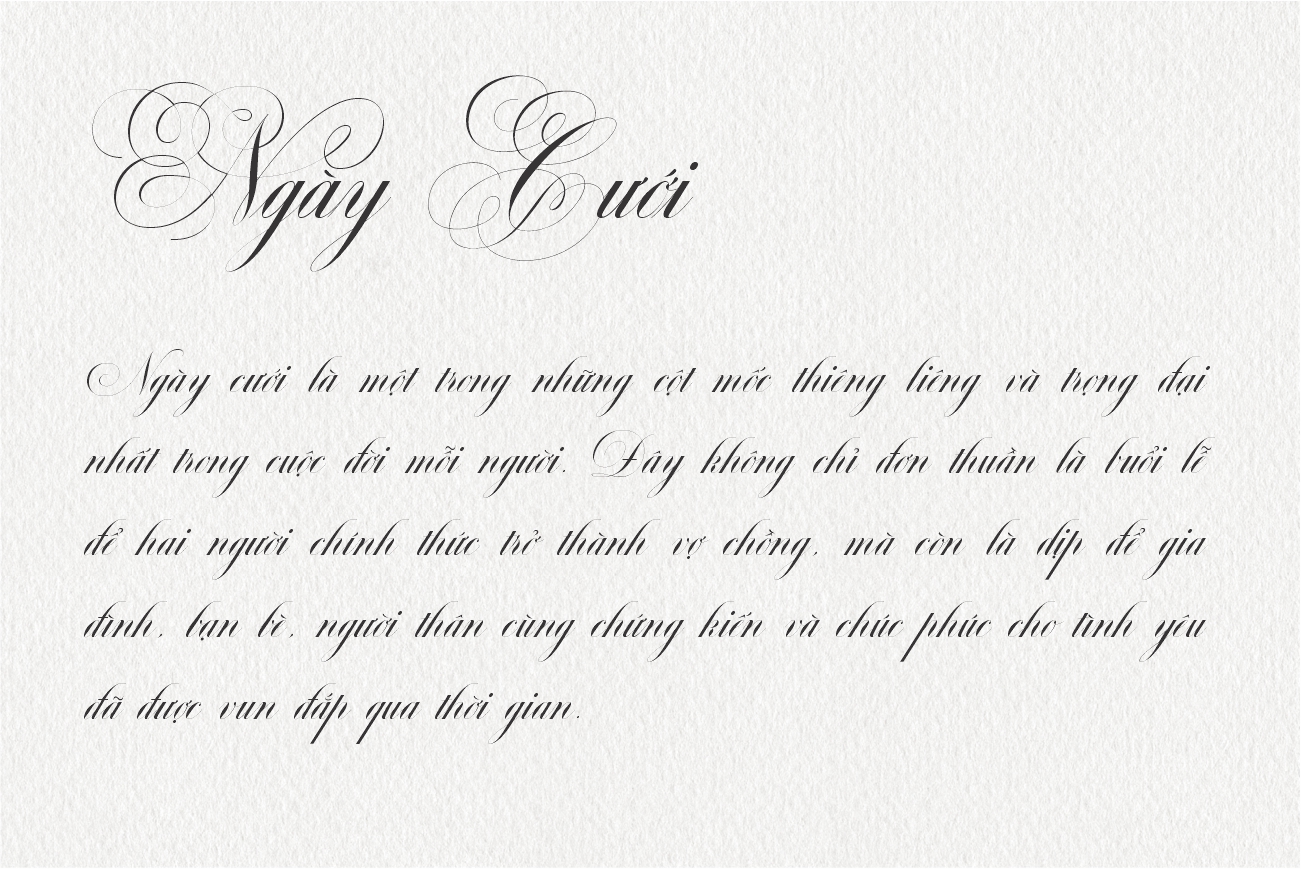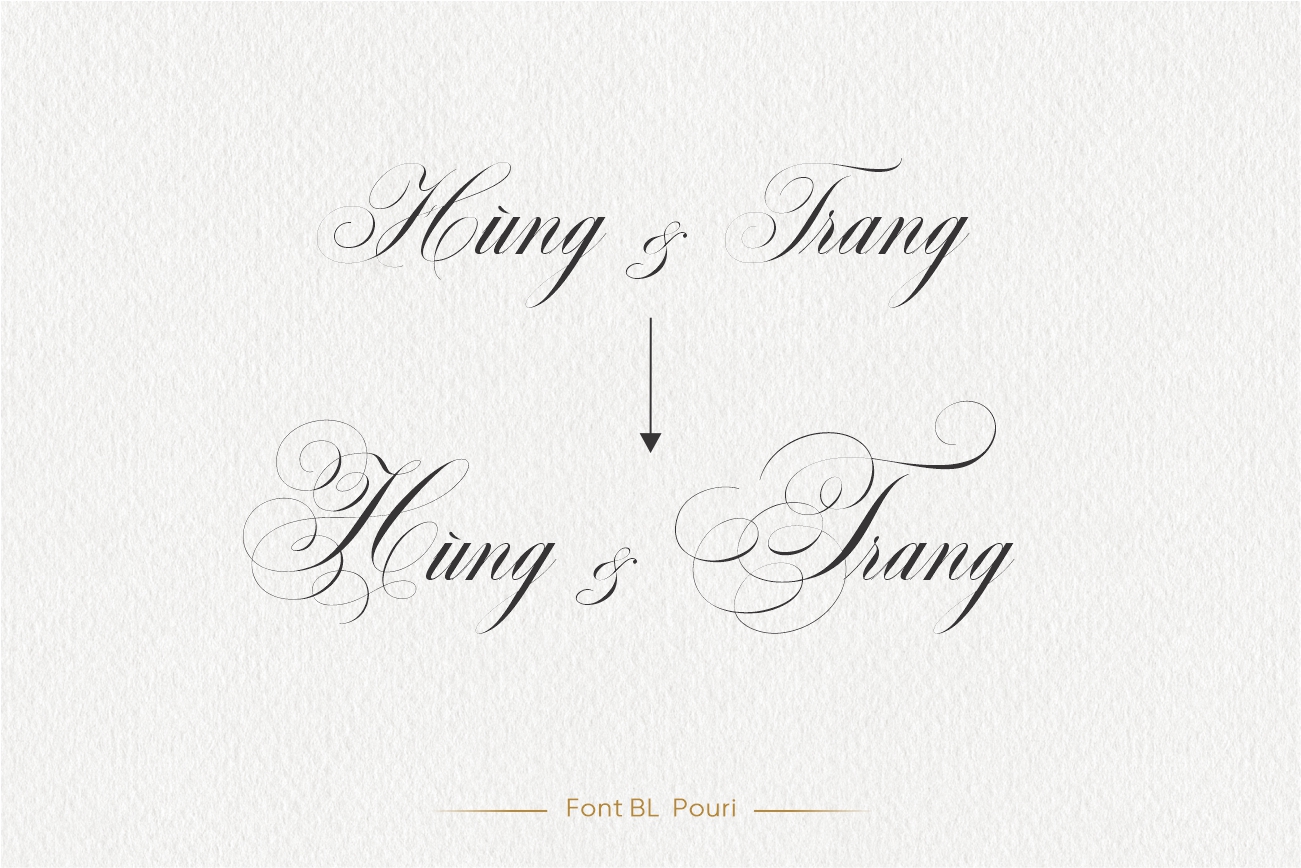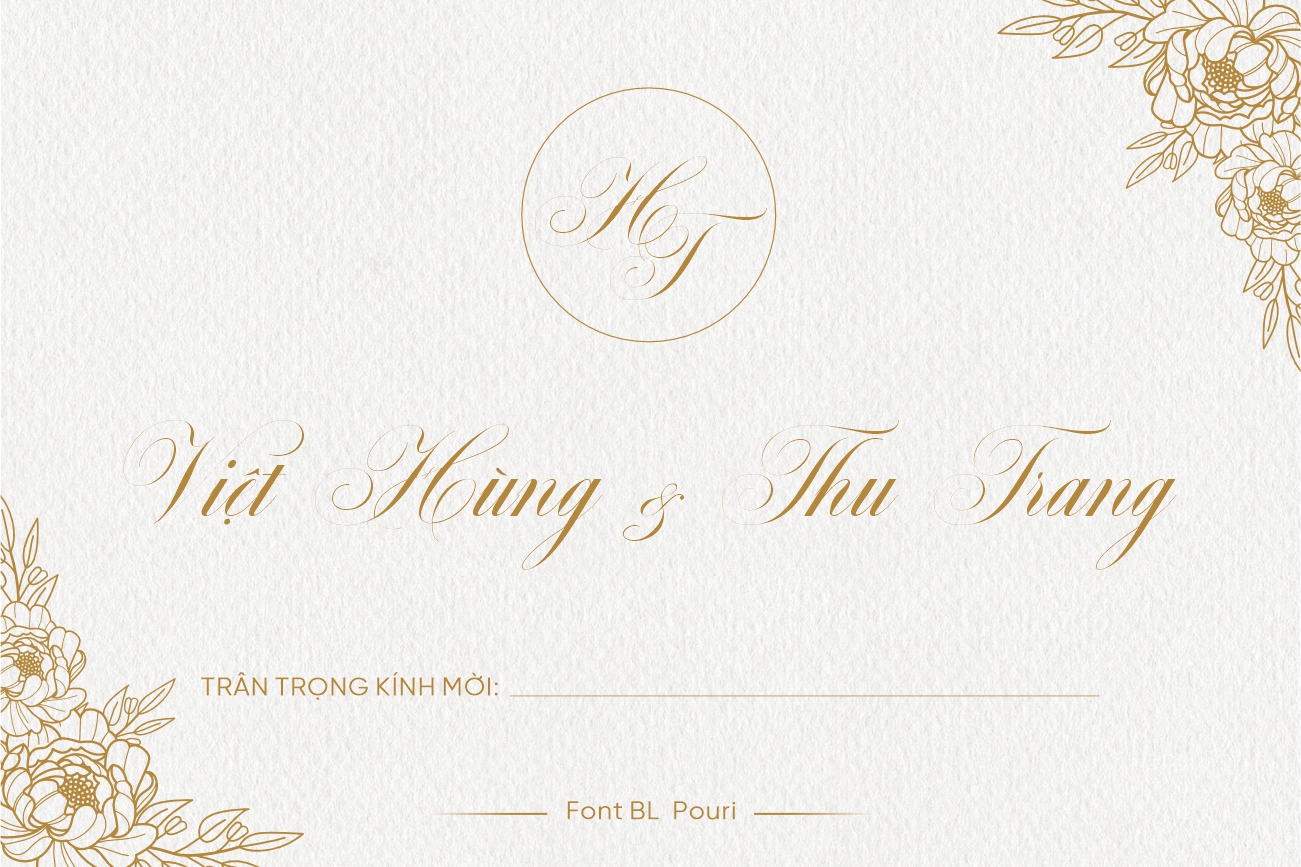
Font chữ calligraphy cho thiệp cưới - BL Pouri Việt hóa
Trong thiết kế cưới hỏi, việc lựa chọn font chữ thiệp cưới phù hợp có thể tạo nên sự khác biệt lớn cho tấm thiệp mời. Một trong những lựa chọn được yêu thích hiện nay là font chữ BL Pouri – mẫu chữ viết tay sang trọng đã được Team BL Việt hóa đầy đủ dấu tiếng Việt, đảm bảo hiển thị hoàn hảo trong mọi dự án thiết kế.
Font chữ BL Pouri thuộc nhóm font chữ calligraphy hiện đại, với các đường nét nét thanh mảnh, mềm mại nhưng vẫn giữ được sự rõ ràng và tinh tế. Đặc điểm nổi bật nhất của font này nằm ở những chi tiết uốn lượn bay bổng, giúp tên cô dâu chú rể hoặc tiêu đề “Ngày cưới” trở nên nổi bật và ấn tượng hơn.
Sự uyển chuyển của font chữ viết tay uốn lượn này mang lại cảm giác gần gũi nhưng vẫn đủ sang trọng để sử dụng trong những sự kiện quan trọng. Vì thế, BL Pouri đặc biệt phù hợp cho font chữ thiết kế thiệp mời, backdrop lễ cưới, menu tiệc hay card cảm ơn. Đây cũng là lý do vì sao nhiều designer đánh giá BL Pouri là một trong những font chữ cưới hỏi việt hóa đáng sở hữu nhất.
Không chỉ giới hạn trong lĩnh vực cưới hỏi, font chữ nghệ thuật này còn có thể ứng dụng cho nhiều dự án thiết kế khác như logo thương hiệu cao cấp, spa, cửa hàng thời trang, mỹ phẩm hoặc các ấn phẩm cần nhấn mạnh sự tinh tế. Với bộ glyphs đa dạng và các ký tự thay thế đẹp mắt, người dùng dễ dàng tùy biến để tạo nên thiết kế độc đáo của riêng mình.
BL Pouri chính là font chữ đẹp cho tên cô dâu chú rể, cho những tấm wedding card mang phong cách thanh lịch, hiện đại. Với phiên bản Việt hóa miễn phí, bạn hoàn toàn có thể sở hữu một font chữ bay bổng việt hóa chất lượng, sẵn sàng đồng hành cùng mọi ý tưởng sáng tạo.